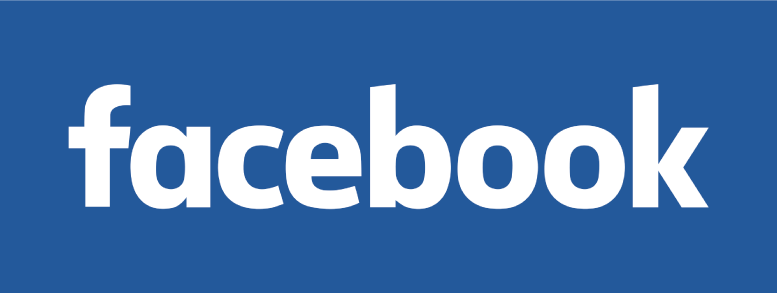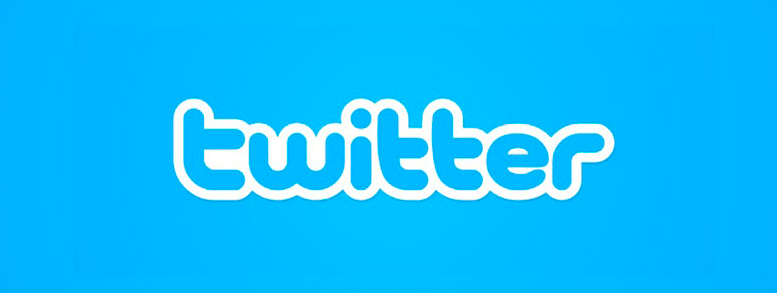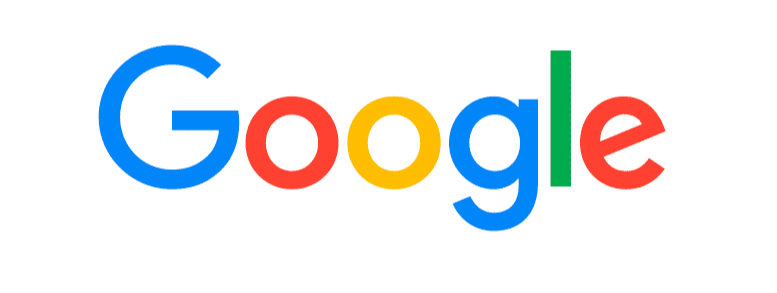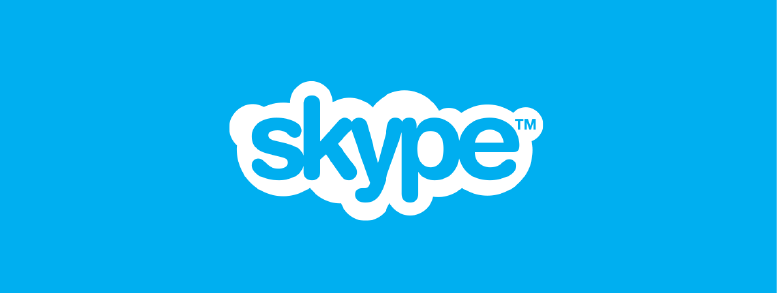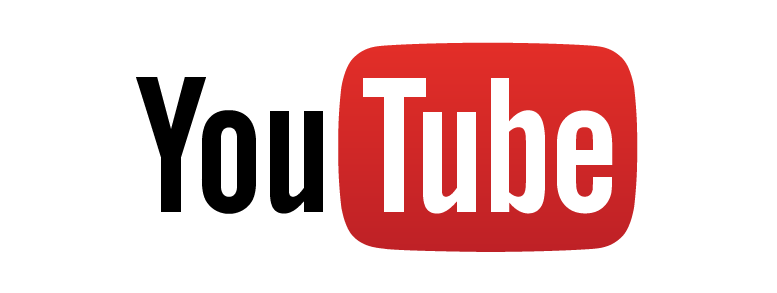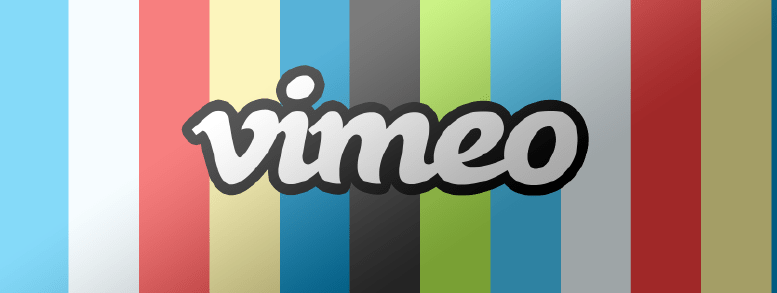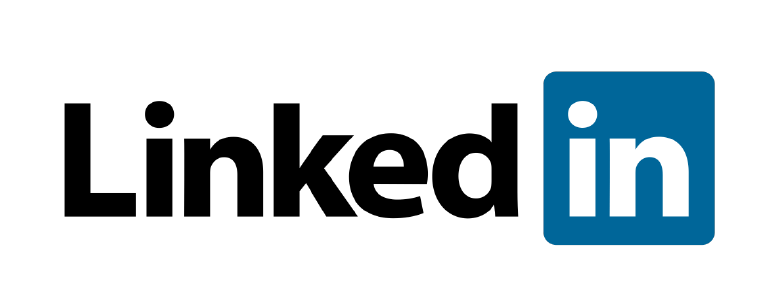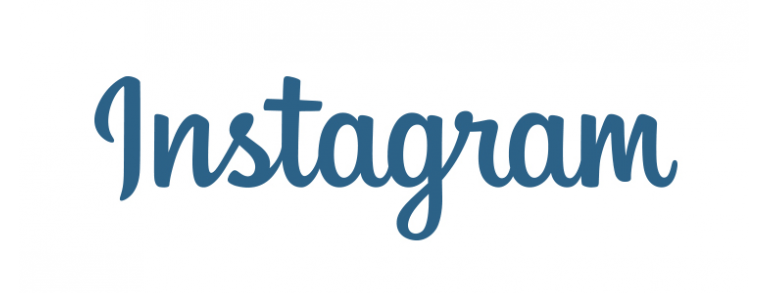
Analizamos las tipografías de 8 logotipos de 8 Redes Sociales.
¿Te encantan las tipografías? ¿te chiflan las redes sociales? ¿te apasionan las listas? ¿te maravillan los enlaces a descargas gratuitas? Pues este post te va a encantar. Sabemos que a la hora de diseñar un logotipo, la elección de la tipografía es lo más complicado, una buena tipografía marca la diferencia. Porque, aunque pase desapercibida, una tipografía puede comunicar más que una imagen, y a veces, lo suficiente sin necesidad de ir acompañada.
Si hablamos del mundo de la publicidad, el marketing, el diseño y el arte, las tipografías suponen un factor esencial (echa un vistazo a este post sobre la psicología de la tipografía). En los campos en los que lo visual juega un papel tan importante a la hora de atraer a un público cada vez más difícil de sorprender, dedicar tiempo a la elección de una buena tipografía, resulta clave para que nuestro diseño tenga éxito.
Si alguna vez has tenido que decantarte por una, y has echado un vistazo a la cantidad de tipografías disponibles que hay en internet, es probable que hayas estado un buen rato tirándote de los pelos. Y seguro que también te has parado delante de algún logo que te atrae inexplicablemente, preguntándote qué tipografía ha usado el diseñador, si eres diseñador seguro que lo haces con todos y cada uno de los logotipos que te encuentras.
En todos los campos, se puede aprender mucho sobre qué es efectivo observando los casos de éxito, por eso me he sumergido en la red para elaborar esta lista de las tipografías usadas en los logotipos de las distintas Redes Sociales, que todo amante de la tipografías debería tener.
Tipografías de las Redes Sociales
Al ver los logotipos de las grandes compañías podrías pensar que la tipografía ha sido diseñada especialmente para el logotipo, o por lo menos que han elegido una fuente dificil de identificar y poco común para destacar frente al resto.
Pero la verdad es que la mayoría de las veces, las marcas más populares, utilizan fuentes muy comunes, detectables sólo por el mayor freak de las tipografías (algo a lo que aspiro).
Arial, Myriad o Trebuchet son algunas de las que se encuentran en más de un logotipo conocido, y son bien sencillas. Como decía mi diseñador preferido Paul Rand “El diseño es simple, por eso es tan complicado”.
Empezamos con la lista ¡qué nervios…!
1. Facebook
La red social que nació como sistema para que los estudiantes de la Universidad de Harvard intercambiasen información (sobre todo acerca de su estado civil), utliza la tipografía Klavika.
El logotipo de Facebook es sólido y rotundo, gracias a cumplir la premisa “menos es más” y la tipografía comparte esta fuerza y consigue apoyar este discurso.
2. Twitter
El sitio donde la gente escribe lo que no se atreve a decir en la calle, (ya sea por miedo a generar controversia o por vergüenza de lo malo que es el chiste que se le acaba de ocurrir), emplea la tipografía Pico Alphabet modificada levemente por razones de legibilidad (la t y la e).
3. Google
El sitio a donde todos recurrimos cuando no sabemos si tenemos razón, utiliza una variación de su tipografía Product Sans (modificando levemente la G y la e), que es muy similar a la Futura.
Google tardó 16 años en rediseñar el logo, al principio algunos sufrimos una semi pataleta, porque ya estabamos acostumbrados, a su logotipo antiguo, con un estilo sencillo, amigable y accesible, los diseñadores sabían esto y quisieron mantener estas cualidades mediante la combinación de la pureza matemática de las formas geométricas con la sencillez de las letras de un libro de colegio. Bien mirado, ¿cómo no lo vas a querer?
4. Skype
Más que una red social es el software favorito de mi madre, que permite comunicarse por video y voz gratis, ¡gratis! ¿en qué estaban pensando?. Bueno…, esta genial compañía utiliza en su logotipo la fuente Helvética Rounded Bold.
En el diseño general, los círculos y las nubes transmiten libertad y naturalidad. Esto, integrado con el estilo de la tipografía y que las letras estén conectadas, reafirma lo que la marca quiere promover, chatear con tus seres queridos libremente estés donde estés.
5. Youtube
El sitio web que permite a miles de personas no tener que encender la tele para entretenerse (y que hace que mi sobrina de 4 años me diga que me suscriba a su canal cada vez que abre un huevo sorpresa), utliza la tipografía Alternate Gothic.
Los colores rojo y negro, y la tipografía de palo seco, consiguen transmitir una imagen dinámica, fresca y sencilla.
6. Vimeo
Sería el hermano mayor de Youtube, sin publicidad, con menos material, pero más profesional, utliza la tipografía Black Rose.
Un look fresco y cuidado que funciona.
7. Linkedin
La mayor red profesional del mundo, se decanta por la sobriedad de la Myriad Pro Bold.
Tanto los colores como la tipografía transmiten una imagen actual, joven y seria.